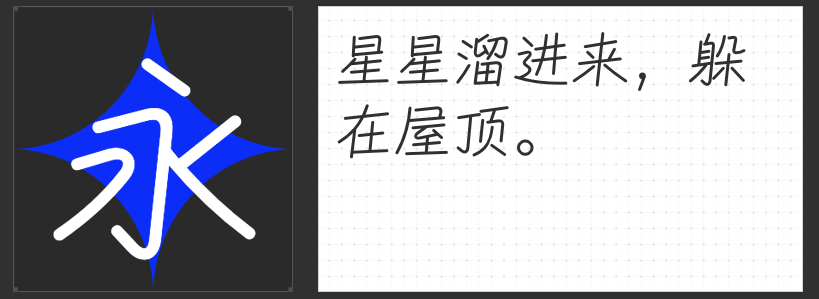
影视设计中的视觉叙事利器:四款风格化字库字体推荐
在影视设计的视觉语言体系中,字体不仅是信息载体,更是情感传递与氛围营造的关键元素。以下四款各具特色的字库字体,以独特的形态语言与视觉张力,为影视画面注入灵魂。
一、励字造桃气圆 大粗
这款以手写感为基底的圆体,通过"上松下紧"的动态结构打破常规字体的平衡感,低重心设计赋予文字扎根画面的稳定感。圆形元素替代部分笔画的创新手法,配合折笔处内外圆角的细腻过渡,让文字在饱满中透出呼吸感。笔画间的"断点"处理既保留了手写字的自然韵律,又通过留白制造出轻盈的视觉节奏,尤其适合需要传递温暖、童趣或生活化场景的影视项目。
二、励字钧线黑简 微黑
全直线构成的字体骨架,以15°黄金倾斜角构建出蓄势待发的动态势能。棱角分明的转折处摒弃冗余装饰,通过精确的笔画粗细对比强化视觉冲击力。这种去繁就简的设计哲学,使文字在保持高辨识度的同时,成为画面中极具现代感的视觉符号,特别适用于科幻、悬疑或需要突出力量感的影视类型。
三、小豆岛默陌秀丽简
取法传统书法却突破碑帖束缚,通过疏密有致的笔画布局构建出独特的视觉韵律。提按分明的笔锋处理既保留书写痕迹的温度,又以现代设计语言重构古典美学。这种刚柔并济的特质,使其成为历史题材、文艺片或需要营造文化厚重感场景的理想选择。
四、喵字摄影体
专为摄影行业打造的定制字体,巧妙融合楷书结构与现代线性设计。通过笔画穿插的呼吸感与适度的留白处理,营造出清新自然的视觉氛围。这种克制而优雅的设计语言,既能完美融入摄影作品,又能在字幕呈现时保持画面整体性,成为影像叙事中不可或缺的视觉注脚。
这四款字体通过差异化的设计语言,构建起从传统到现代、从灵动到锋利的完整视觉谱系,为影视创作者提供了丰富的情感表达工具。选择恰当的字体,即是选择与画面共鸣的视觉频率,让文字成为撬动观众情感的隐形杠杆。